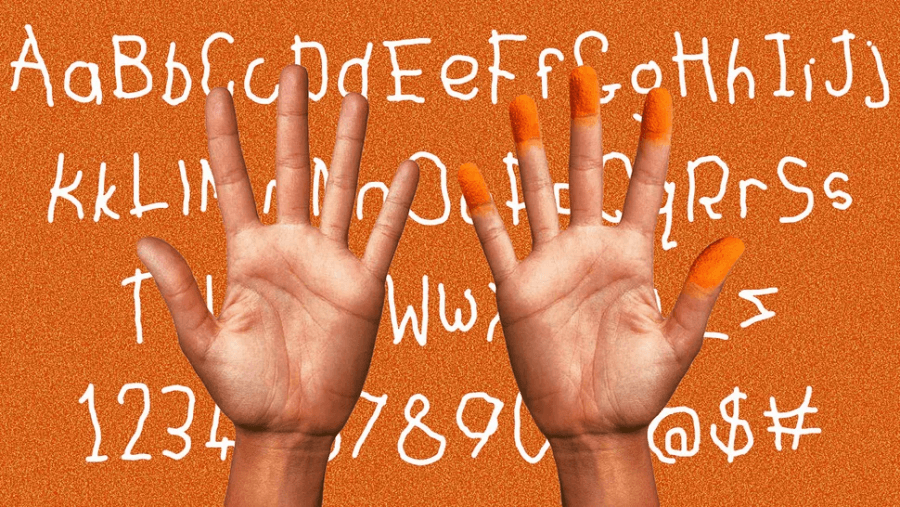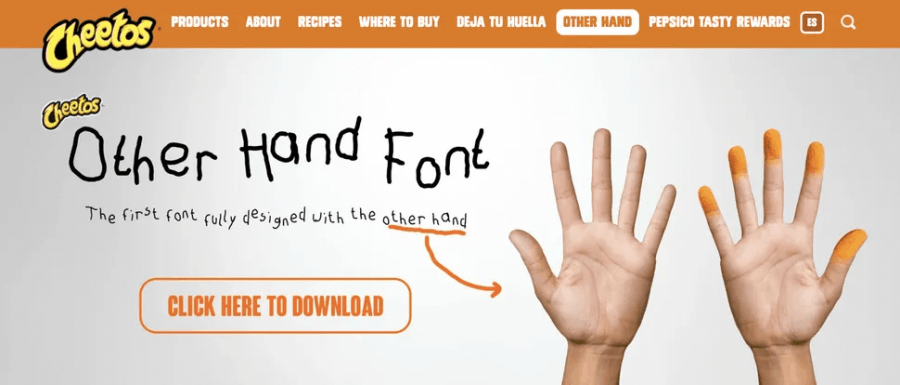
치토스 폰트가
주목받고 있다.
신의 한 수 인가?
무리수인가?
불완전함의 매력으로
브랜드 정체성 강화한 치토스 폰트
치토스 폰트가
주목받고 있다.
신의 한 수 인가?
완벽함의 시대에, 치토스가 던진 ‘치즈 가루 묻은’ 폰트
세련됨과 완벽한 디테일에 집착하는 것이 당연한 시대다. 그러나 치토스가 최근 선보인 장난스럽고 유머러스한 폰트가 오히려 신선한 충격을 주며 주목받고 있다. 마치 일부러 엉성하게 휘갈긴 듯한 이 손글씨 폰트는 단순히 마케팅의 전략적 시도일까, 아니면 디자인적 모험일까? 어쩌면 이 어설픈 매력이야말로 치토스다운 탁월한 전략일지 모른다.
모든 타이포그래피 디자이너는 한목소리로 말한다. "폰트는 브랜드 아이덴티티를 형성하는 강력한 도구입니다." 폰트 하나만으로도 브랜드의 개성을 명확히 드러내고 메시지의 톤을 결정할 수 있다는 것이다. 이 점에서 치토스는 제대로 된 한 수를 던졌다. 아니, 정확히 표현하면, ‘치즈 가루가 묻은 손으로 휘갈겨 쓴 듯한’ 폰트를 탄생시켰다.
이 폰트는 디자이너들이 일부러 반대손으로 완성한 작품이다. 비록 실제로 치즈 가루가 묻어 있지는 않겠지만, 치토스를 먹을 때의 지저분하고 장난기 넘치는 감성이 생생히 담겨있다. 결국, 이 폰트는 브랜드의 정체성을 직관적이고 효과적으로 시각화한 것이다. 엉망진창이면서도 유쾌하고, 무엇보다 진정한 의미에서 인간적이다.
대부분의 브랜드가 일관되고 정돈된 이미지 유지를 최우선으로 하는 반면, 치토스는 오히려 ‘리얼함’이라는 가치를 정확히 꿰뚫었다. 디지털화가 빠르게 진행될수록 사람들은 점점 더 진짜 같은, 인간적인 요소에 목마르기 마련이다.
"완벽함보다 중요한 것은 ‘진짜’의 감성"
이 흐름은 다양한 분야에서 감지된다. 단지 유행이나 트렌드를 넘어, "진정성에 대한 인간의 본능적 갈망"으로부터 비롯된 현상이다.
치토스 폰트의 삐뚤빼뚤한 손글씨 스타일과 유머러스한 느낌은 마치 디자이너들이 사무실에서 치토스를 먹으며 농담처럼 장난삼아 만들었을 것 같은 생동감을 전달한다. 그리고 실제로 그렇게 만들어졌다고 해도 놀랍지 않을 정도이다.
오늘날 브랜딩에서 가장 중요한 요소는 ‘인간적 연결’이다. 브랜드는 단순히 로고나 시각적 기호의 조합을 넘어서 소비자와 감정적 유대감을 형성할 때 완성된다. 그러나 자동화와 효율성을 추구하는 현대의 흐름 속에서 많은 브랜드가 이 본질적인 부분을 놓치곤 한다.
최근의 디자인 트렌드는 미니멀리즘과 정교한 세련미에 집중한다. 그러나 때때로 과도한 정제는 오히려 브랜드만의 고유한 개성과 인간적인 요소를 희미하게 만드는 부작용을 낳기도 한다.
반면, 치토스는 우리가 여전히 인간적인 감성과 유머, 그리고 불완전함의 매력을 여전히 사랑한다는 사실을 정확히 포착하고 있다.
브랜드 아이덴티티 또한 이제는 더욱 유연한 형태를 띠기 시작했다.
과거처럼 엄격한 브랜드 가이드라인을 고집하는 대신, 브랜드가 유동적이고 창의적으로 변화하며 적응할 수 있는 "유연한 아이덴티티(flexible identity)"가 중요해진 시대다. 핵심은 일관성을 유지하면서도 창의성과 유머를 놓치지 않는 것이다.
물론 브랜드 가이드라인 자체가 필요 없다는 의미는 결코 아니다. 디자인 전문가라면 가이드라인의 중요성을 누구보다도 잘 알 것이다. 다만 이제는 가이드라인을 엄격한 규칙으로 보기보다는 상황에 맞게 유연하게 활용 가능한 지침으로 바라볼 필요가 있다.
치토스의 새로운 폰트는 바로 이러한 시대적 흐름을 상징한다. 지나치게 정돈되고 깔끔한 디자인이 가득한 세상에서, 이 엉뚱하고 자유분방한 폰트는 마치 신선한 공기와 같다. 아니, 더 정확히 표현하자면, ‘치즈 가루가 흩날리는 바람’이라고 해야 할 것이다.
반대 손으로 쓴듯한 치토스 폰트
이 폰트는 인간적인 연결의 힘과 불완전함의 아름다움, 그리고 무엇보다도 결국 맛있고 유쾌한 치토스의 본질적인 매력을 생생히 담아내고 있다.